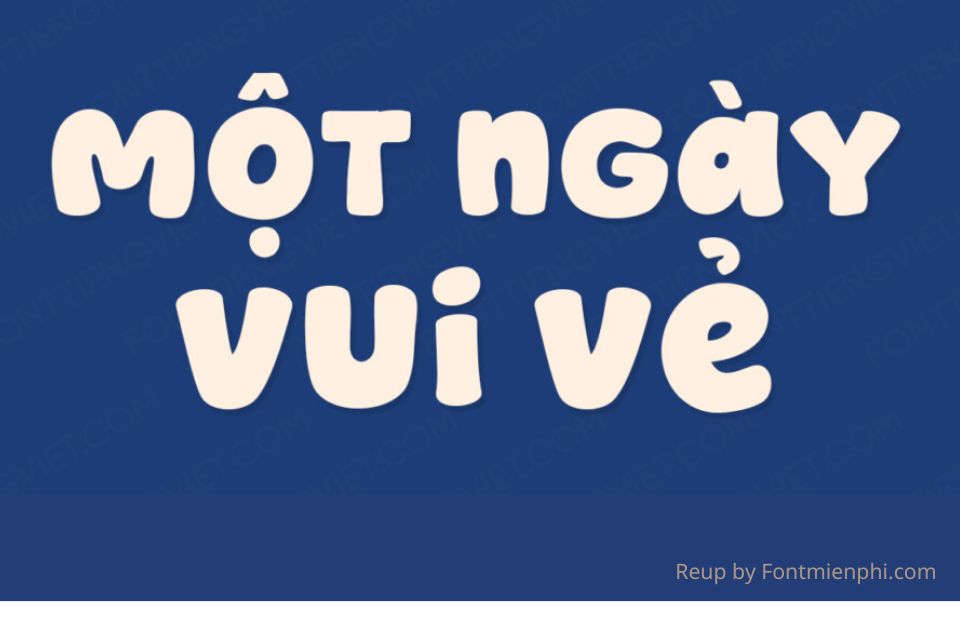
Font Việt hóa 1FTV VIP Creamy Chicken đẹp, vui nhộn
Font Việt hóa 1FTV VIP Creamy Chicken – Font hoạt hình bo tròn, vui nhộn và nổi bật
Giới thiệu Font Việt hóa 1FTV VIP Creamy Chicken
1FTV VIP Creamy Chicken là font chữ Việt hóa mang phong cách hoạt hình vui nhộn, nổi bật với những đường nét dày, mềm mại và bo tròn. Kiểu dáng chữ tạo cảm giác thân thiện, đáng yêu nhưng vẫn đủ mạnh để thu hút sự chú ý khi sử dụng trong các tiêu đề lớn.
Creamy Chicken đặc biệt phù hợp với những thiết kế cần truyền tải sự trẻ trung, hài hước và tràn đầy năng lượng. Chỉ cần kết hợp font với một bảng màu tươi sáng, bạn có thể nhanh chóng tạo nên những mẫu poster, banner, logo hoặc hình ảnh quảng cáo nổi bật.
Phiên bản 1FTV VIP Creamy Chicken Việt hóa đã được bổ sung hệ thống ký tự tiếng Việt, giúp người dùng nhập nội dung có dấu thuận tiện hơn trong quá trình thiết kế.
Phong cách thiết kế nổi bật Font Việt hóa 1FTV VIP Creamy Chicken
Creamy Chicken thuộc nhóm font trang trí theo phong cách Fancy và Cartoon. Font gốc được thiết kế bởi MJType, sở hữu kiểu chữ đậm, vui nhộn và phù hợp với các dự án thiết kế mang tính giải trí.
Các ký tự có hình dáng mềm, mập và tương đối ngộ nghĩnh. Khoảng cách chữ thoáng vừa phải, giúp phần tiêu đề dễ đọc ngay cả khi sử dụng trên hình ảnh có nhiều màu sắc.
Một số đặc điểm nổi bật của font:
• Nét chữ dày, mềm mại và bo tròn.
• Phong cách hoạt hình vui vẻ, đáng yêu.
• Khả năng tạo điểm nhấn tốt cho tiêu đề.
• Hỗ trợ chữ hoa, chữ thường, chữ số và dấu câu.
• Phù hợp với các thiết kế hướng đến trẻ em và giới trẻ.
Font không phù hợp để trình bày những đoạn văn bản dài. Thay vào đó, Creamy Chicken phát huy hiệu quả tốt nhất khi được sử dụng cho logo, slogan, tiêu đề hoặc những cụm nội dung ngắn cần làm nổi bật.
Font 1FTV VIP Creamy Chicken phù hợp với thiết kế nào?
Nhờ phong cách mềm mại và vui nhộn, font có thể ứng dụng trong nhiều chủ đề thiết kế khác nhau.
Thiết kế logo và nhận diện thương hiệu
Creamy Chicken là lựa chọn phù hợp cho các thương hiệu có phong cách trẻ trung như cửa hàng đồ ăn nhanh, tiệm bánh, quán trà sữa, cửa hàng đồ chơi, thương hiệu thời trang trẻ em hoặc kênh nội dung giải trí.
Kiểu chữ đậm giúp tên thương hiệu dễ nhận diện, trong khi các góc bo tròn tạo cảm giác gần gũi với khách hàng.
Thiết kế poster ẩm thực Font Việt hóa 1FTV VIP Creamy Chicken
Ngay từ tên gọi Creamy Chicken, font đã gợi liên tưởng đến những nội dung liên quan đến đồ ăn, món ngon và nhà hàng. Bạn có thể sử dụng font để thiết kế:
• Poster món ăn.
• Menu nhà hàng.
• Bảng giá đồ ăn nhanh.
• Bao bì thực phẩm.
• Banner khai trương.
• Chương trình khuyến mãi.
• Hình ảnh quảng cáo trên mạng xã hội.
Khi kết hợp với màu vàng, đỏ, cam hoặc xanh lá, font có thể tạo nên phong cách quảng cáo ẩm thực rất bắt mắt.
Font Việt hóa 1FTV VIP Creamy Chicken đẹp, vui nhộn
Nội dung dành cho trẻ em Font Việt hóa 1FTV VIP Creamy Chicken
Những đường nét tròn trịa và thân thiện giúp Creamy Chicken phù hợp với sách thiếu nhi, lớp học, trung tâm ngoại ngữ, đồ chơi, chương trình vui chơi và các sản phẩm dành cho trẻ nhỏ.
Font có thể được sử dụng cho tiêu đề truyện tranh, bảng chữ cái, thiệp sinh nhật, bảng tên lớp học hoặc hình ảnh trang trí sự kiện.
Thumbnail và nội dung mạng xã hội
Font Việt hóa 1FTV VIP Creamy Chicken có khả năng hiển thị nổi bật trên kích thước nhỏ, phù hợp để làm chữ trên thumbnail YouTube, video TikTok, Facebook Reels, Instagram hoặc bài đăng quảng cáo.
Để nội dung dễ đọc hơn, bạn nên sử dụng màu chữ tương phản với nền, thêm viền chữ hoặc đổ bóng nhẹ.
Tổng kết
Font Việt hóa 1FTV VIP Creamy Chicken là lựa chọn thú vị dành cho những nhà thiết kế đang tìm kiếm một kiểu chữ đậm, bo tròn và mang phong cách hoạt hình vui nhộn.
Font đặc biệt phù hợp với logo, poster ẩm thực, bao bì đồ ăn, nội dung trẻ em, thumbnail YouTube và hình ảnh quảng cáo trên mạng xã hội. Khả năng hỗ trợ tiếng Việt giúp quá trình sáng tạo nội dung trở nên thuận tiện, hạn chế tình trạng lỗi dấu hoặc thiếu ký tự.